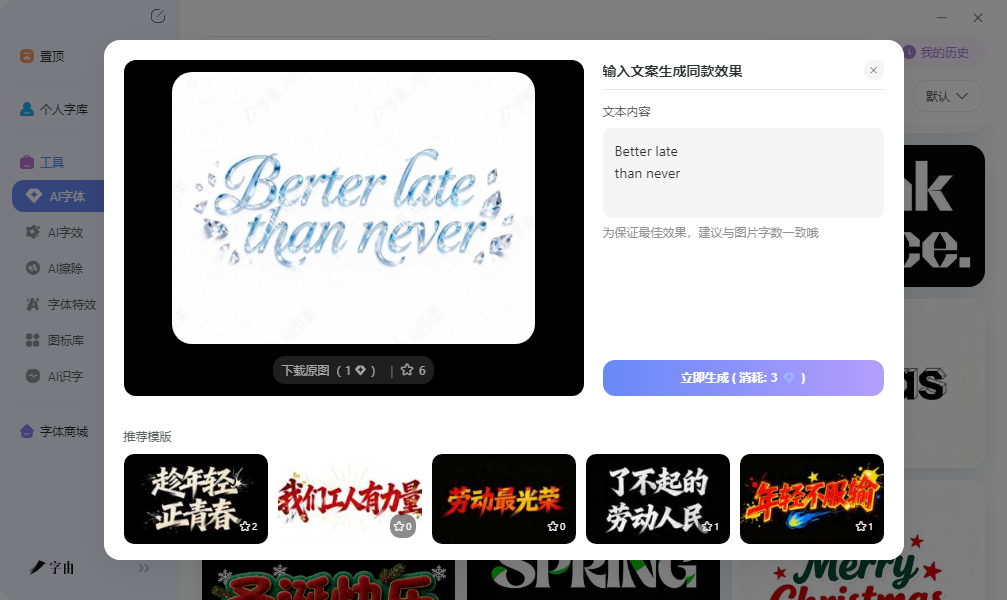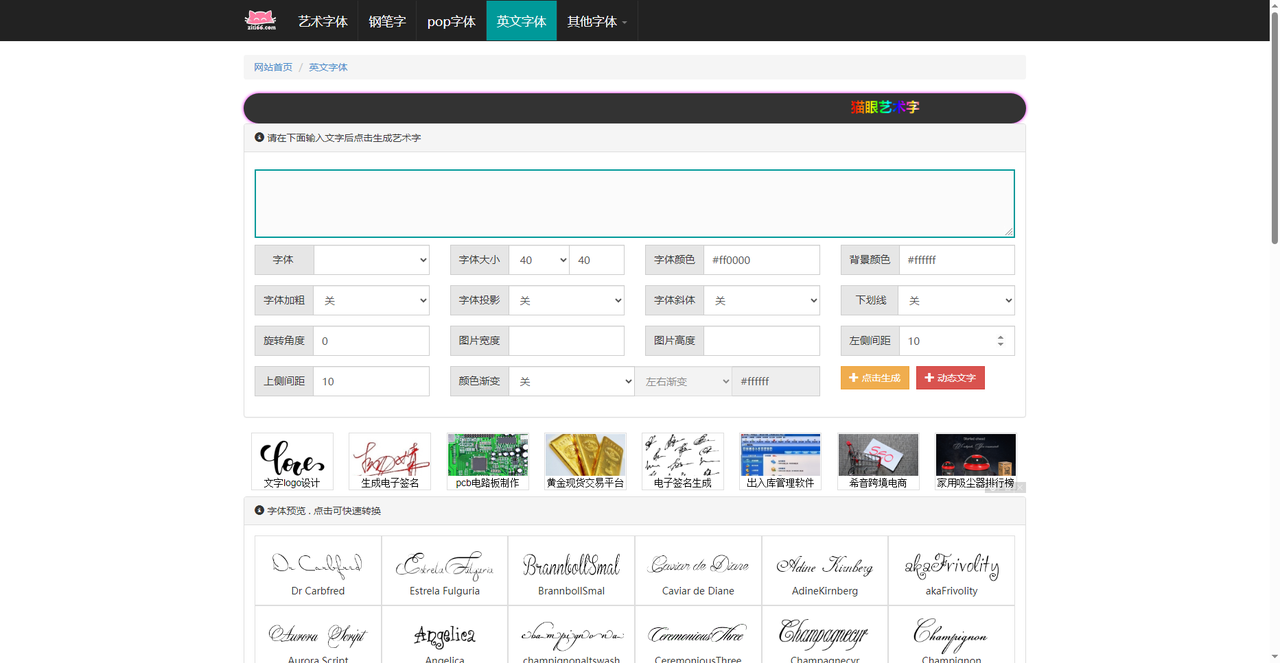
还在找英文字体生成器?这几个网站输入文字秒变特效
做英文Logo差一个有冲击力的金属标题,或者社交媒体封面缺一行吸引眼球的花体字。每次打开PS,翻遍字体列表就是那几个默认的老面孔。想加点特效,外发光、内阴影、渐变叠加调了半天,出来的效果还是不对。其实,生成这种高清可商用的艺术字图,有更省事的法子。今天实测了5款在线英文字体生成器,有直接用现成模板一键生成的,有让用户慢慢调参数的,也有专攻花体字复制粘贴的。按需自取,总有一款能帮你把普通英文变好看。
市面上不少英文字体生成器,生成的图要么分辨率低,要么字体来源不明、不敢商用。字由的AI字体功能走的路线是把这些问题都打包解决掉。它提供400多套现成模板,配合平台内的正版字体库,不用下载安装,也不用自己调参数。
打开字由官网或客户端,在“字体工具”下找到“AI字体”,里面按场景和风格分好了类:做电商主图有“电商促销”分类,冲击力强的粗体字已经配好了金色渐变和夸张描边,替换文案就能直接用;做夜店活动海报,点“霓虹灯”分类,30多款红蓝紫配色的发光字效果,有些还模拟了真实灯管的弯曲路径。想给咖啡店做个品牌标题,手写书法风里也有十几种不同笔触的模板。如果要做花体英文,搜索栏输入“花”“装饰”“英文花体”,系统会筛出带藤蔓、花朵装饰的模板。
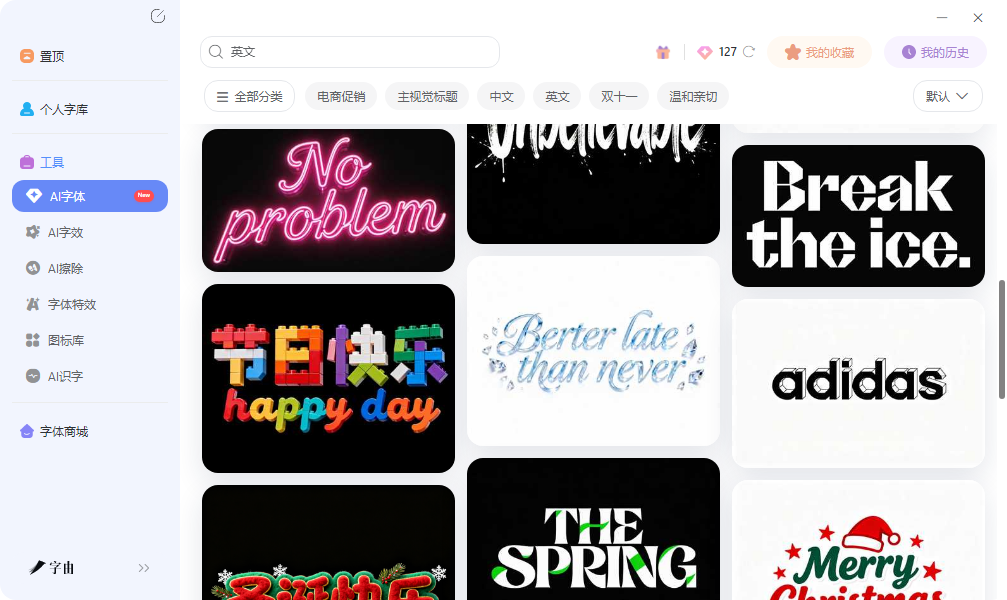
操作无非三步:选模板、打字、下载:鼠标只要移到模板,预览图立刻换成本文的文案,不用点进去就知道适不适合。看中哪款点“做同款”,在编辑器里把英文换成自己的文案。注意尽量保持字母数量与模板一致,生成的结构最协调。点“立即生成”,20到30秒左右就能拿到一张高清图片。下载时选透明背景PNG,拖进PS、剪映或其他设计软件里直接用,不用额外抠图。
2、猫眼艺术字
第二个工具是猫眼艺术字。它提供“凉如三月”“月亮船”等多种英文字体预设,参数选项包括字体大小、颜色、背景色、加粗、投影、斜体、旋转角度、图片尺寸、边距、颜色渐变等。跟前面的一键生成不一样,这个工具更像一个简配版PS文字工具。对颜色、大小有精确要求,比如标题色值必须和品牌Logo一致,在这里可以直接手动输入色值;想让文字斜着排或者带点阴影,点几下鼠标就行。比PS简单很多,又比纯模板生成器灵活。页面下方有“字体预览”区,列出“Dr Carbfred”“EstrelaFulguria”“BranbollSmal”等多种预设字体,看中哪个点一下就用,省得去字体列表里一个个翻。适合那些对效果有自己的想法、但又不想学PS的用户。
3、在线字体转换器
第三个网站是一个综合型的在线字体转换器。它的最大特点是分类细致:虎年精选、海报字体下载、电商广告专用、书法字体、花体、简约字体、节日专属、卡通可爱等。这个站还有一个“手工签名设计”功能,输入英文名可以生成连笔签名样式。在线转换器部分,可以选择“AprilFlowers”“Dhanikan”“Halimun”等英文字体,调节大小、颜色、背景透明后开始转换,生成图片下载。适合电商运营、自媒体小编这类需要经常出图的用户——在“电商广告专用字体”里直接翻,省去在海量字体库里瞎逛的时间。
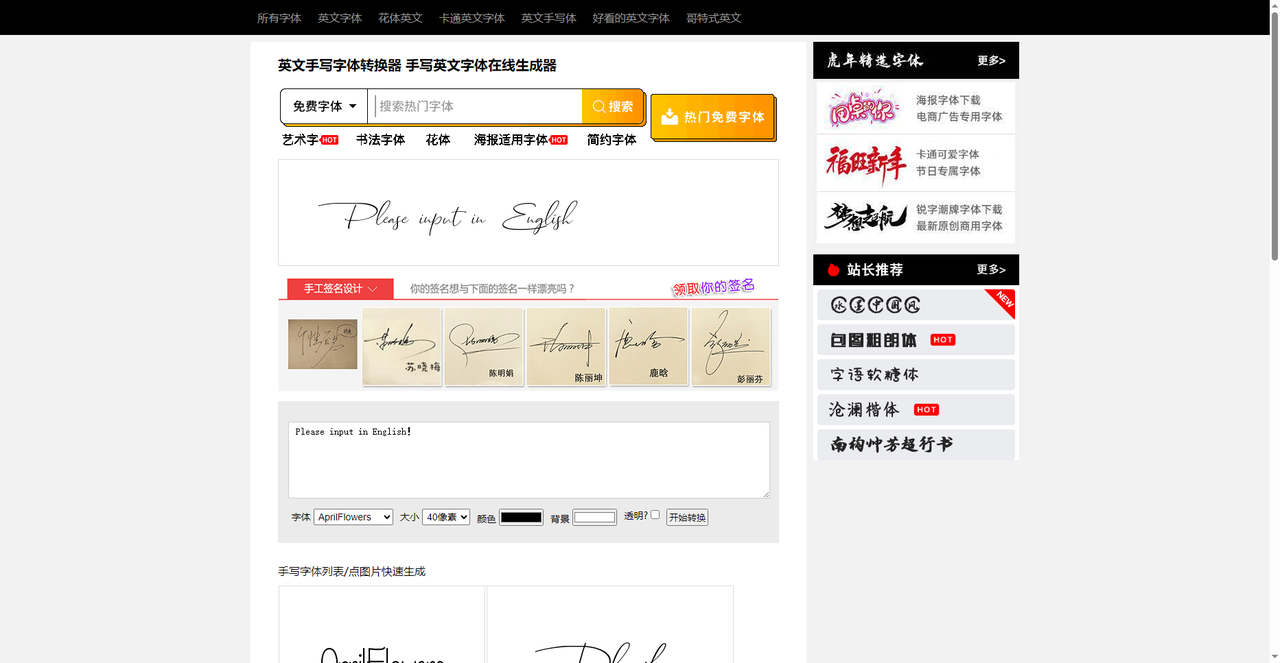
4、花体英文字体生成器
第四个工具是一个专门做花体英文字体的在线生成器。它提供超过100种花体英文样式,包括漫画插图、斜体、手写体、数学公式、双线体等多种分类。操作简单:输入英文,点击生成,3秒内出现几十种不同风格的预览效果,点“复制”按钮就能把花体字复制到剪贴板。然后直接粘贴到微信、抖音、Instagram、Discord等任何支持文本输入的地方。不需要下载图片,不需要安装字体,完全免费,无需注册。适合只想在社交平台发花体字文案、改游戏昵称的普通用户,几秒钟搞定。
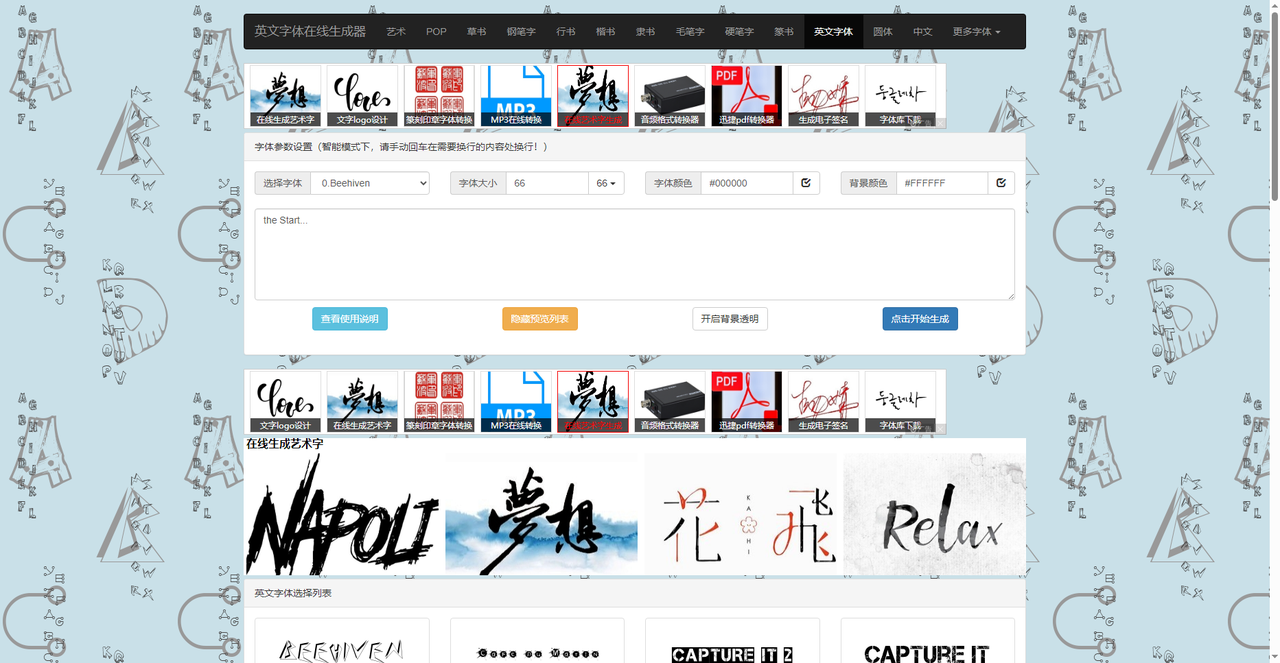
5、英文手写字体转换器
第五个工具是一个英文手写字体转换器。它提供“AprilFlowers”“LoveHurts”“Holland”等多种手写风格字体预设。操作方式很简单:输入英文,选择想要的字体样式——有的像钢笔随手写的草书,有的像圆润可爱的卡通手写,有的带连笔效果。可以调节大小、颜色、背景透明度,点击“开始转换”就能生成图片。页面下方还有“手写字体列表”,点图片快速生成。它的特色是专注于“手写感”,适合做邀请函、个人博客标题、手账风格的配图。
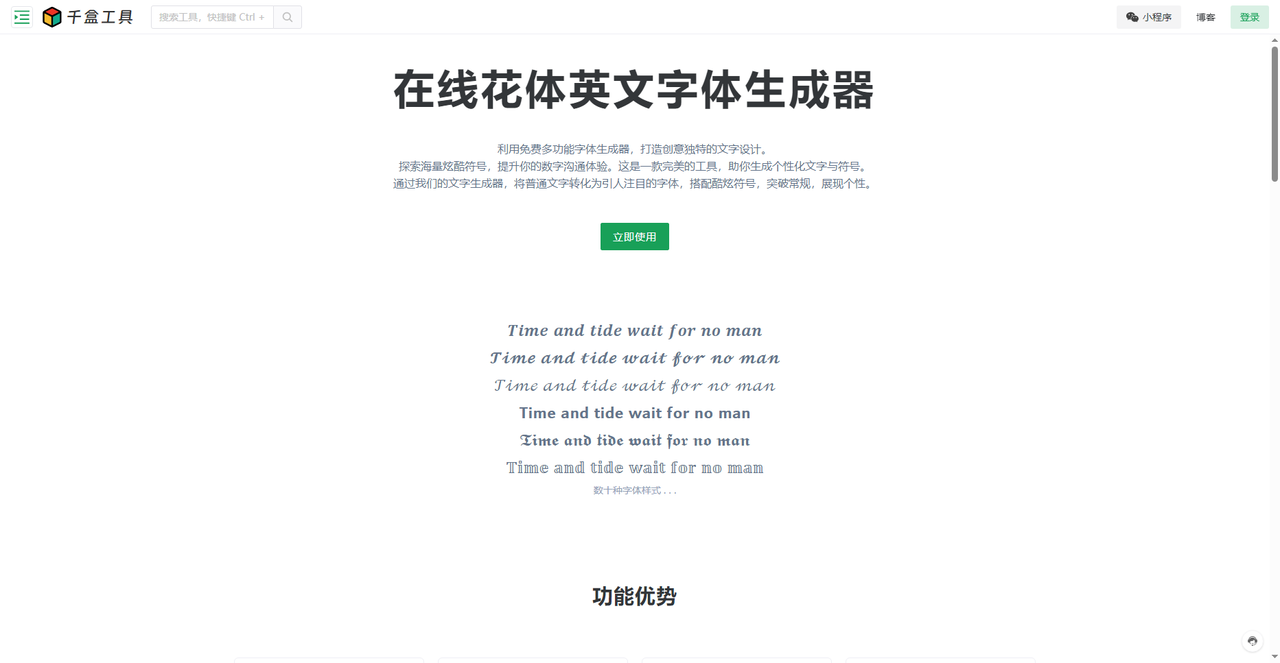
五个英文字体生成器,对应不同的使用场景。字由最适合设计师和需要可商用艺术字图的人,多套AI模板10秒出图,出图清晰;猫眼艺术字支持颜色、大小、投影、旋转自由调节,适合追求精细控制的用户;在线字体转换器按场景分类齐全,电商、海报、节日应有尽有,适合按项目快速找风格;花体英文字体生成器一键复制粘贴,适合社交平台耍个性;英文手写字体转换器专注手写感,适合邀请函和手账风格。缺什么效果,按项目需求挑对应的门就行。